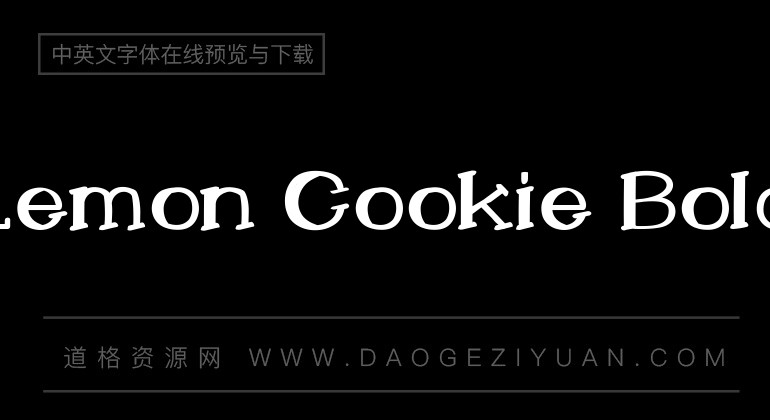
Lemon Cookie Bold 字体是一款由 Fontfabric 公司设计的手写体字体,它具有独特的外观,活泼而又温柔的风格,适用于多种场景,比如标题、标识、海报、活动等。其特点是:自然的笔触,大胆的线条,清晰的形状,多样的类型,以及充满活力的风格。Lemon Cookie Bold 字体可以用于各种类型的设计项目,是一款动感而又充满活力的字体。内容介绍
Lemon Cookie Bold是一款非常不错的手写艺术字体,具有很好的视觉感,适合于文化类的宣传设计、商业类品牌的广告和产品包装设计以及个性化文字排版等较多场景。